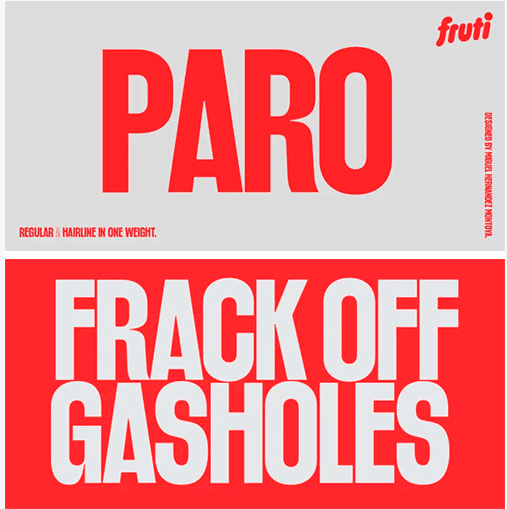
Paro Font
Paro Эрнандеса Монтойи - это голос протеста с народными корнями. Вдохновленный Woodtype и нарисованными вручную буквами бригад художников-монументалистов и политическими плакатами. Тяжелый и сжатый, дает мощный цвет в ударных композициях, уравновешенный легкими диакритическими знаками и символами.